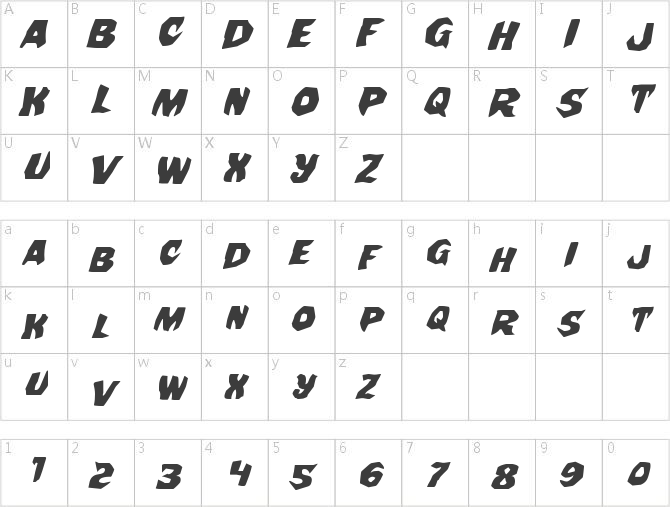
Nightchilde Expanded Italic 詳情頁
Nightchilde Expanded Italic字體字庫是一款讓人賞心悅目、百看不厭的英文字體,適合各類廣告和產(chǎn)品包裝設(shè)計應(yīng)用,字體大小0.05MB,格式為ttf字體,上傳用戶是華大文化傳媒,作者/版權(quán)方為未知